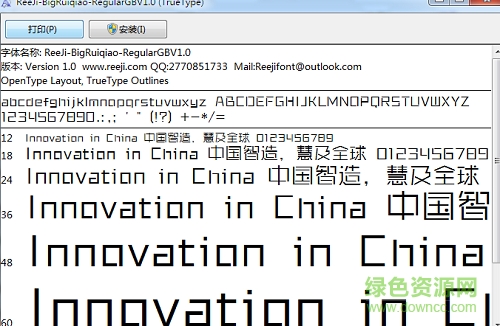
bigruiqiaogb1.0字體是一款充滿靈動氣息的銳字銳線俏皮簡,筆畫特征突出,可以用在辦公文檔、廣告設(shè)計、網(wǎng)頁設(shè)計等方面,喜歡創(chuàng)意字體就來綠色資源網(wǎng)下載吧!
是一款無線襯托的裝飾體,線條活潑,線條富有節(jié)奏與靈動,有點與線的完美結(jié)合,同時字型通氣連貫,具有設(shè)計感與現(xiàn)代,感突出全新的筆畫特征。